【パチンコ】新台入替 psd jpg png 素材 エヴァ風フォント&メカ加工
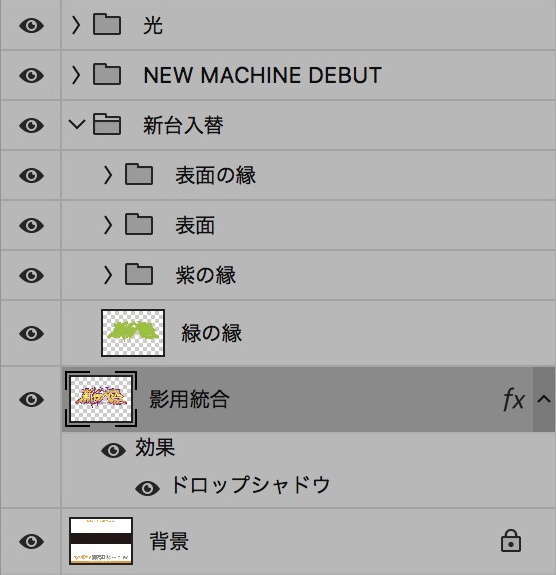
パチンコホール様向け【新台入替】タイトル素材です。 フォトショップデータはなるべく細かくレイヤー分けしてあります。 デザイン制作の時間短縮や、文字装飾の作り方の参考にご利用ください。 ※文字の打ち変えはできませんので、ご注意ください。 ※ダウンロード販売データとなります。